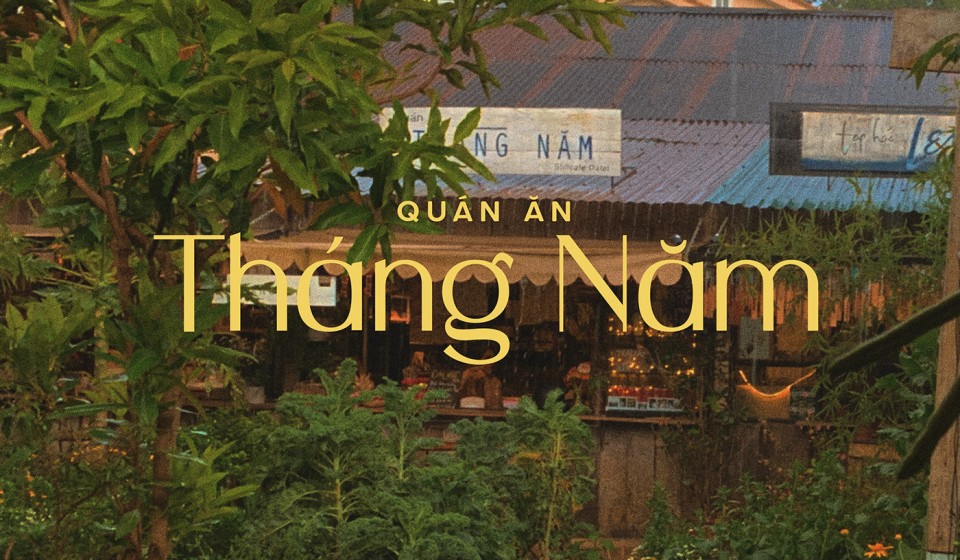
Giới thiệu bộ Font tiếng việt Dalat Sans và Dalat Sans Cap
Trong thế giới đồ họa hiện đại, việc tìm kiếm một bộ Font Chữ mang đậm hơi thở nghệ thuật cổ điển nhưng vẫn giữ được nét tinh tế là điều không hề dễ dàng. Font tiếng việt Dalat Sans và Dalat Sans Cap chính là giải pháp hoàn hảo cho những ai yêu mến vẻ đẹp hoài niệm của thành phố sương mù Đà Lạt. Được lấy cảm hứng từ những biển hiệu vẽ tay cũ kỹ, bộ phông chữ này mang đến một cảm giác mộc mạc, chân thực và tràn đầy cảm xúc cho mọi tác phẩm thiết kế từ poster đến bìa sách giáo khoa.
Đặc điểm nổi bật của Font tiếng việt Dalat Sans và Dalat Sans Cap
Sự kết hợp hoàn hảo giữa hiện đại và cổ điển
Bộ phông này bao gồm hai phiên bản chính giúp người dùng linh hoạt hơn trong trình bày. Dalat Sans tập trung vào sự thanh thoát, dễ đọc ở định dạng chữ thường, trong khi Dalat Sans Cap lại gây ấn tượng mạnh mẽ với các ký tự in hoa vững chãi. Điểm đặc biệt nhất là cả hai đã được Việt hóa hoàn chỉnh, hỗ trợ đầy đủ các dấu tiếng Việt mà không gặp lỗi hiển thị. Điều này giúp các bạn học sinh và giáo viên dễ dàng ứng dụng vào các bài thuyết trình hay báo tường một cách chuyên nghiệp nhất.
Ứng dụng đa dạng trong học tập và sáng tạo
Không chỉ giới hạn trong thiết kế chuyên nghiệp, Font tiếng việt Dalat Sans và Dalat Sans Cap còn cực kỳ phù hợp cho môi trường giáo dục. Với đường nét rõ ràng và mang tính thẩm mỹ cao, bộ font này giúp các tài liệu giảng dạy trở nên sinh động và gần gũi hơn. Các bạn trẻ có thể sử dụng chúng để làm thiệp chúc mừng, thiết kế áo lớp hoặc trang trí blog cá nhân với phong cách retro độc đáo.